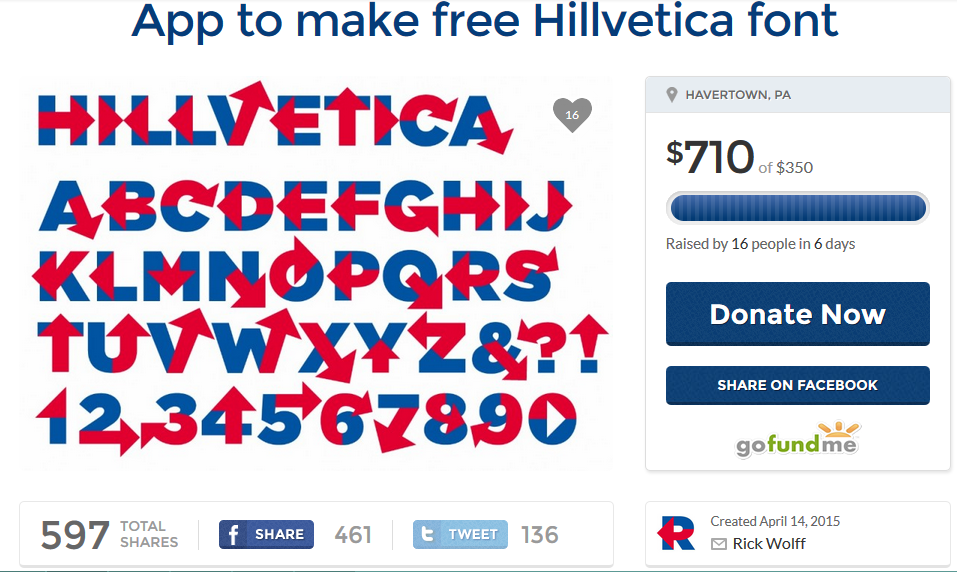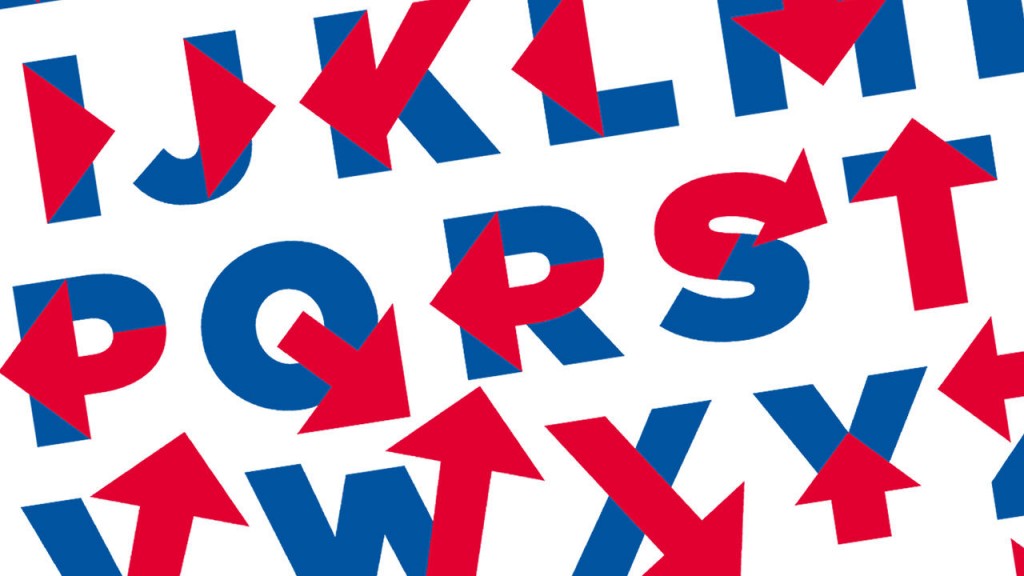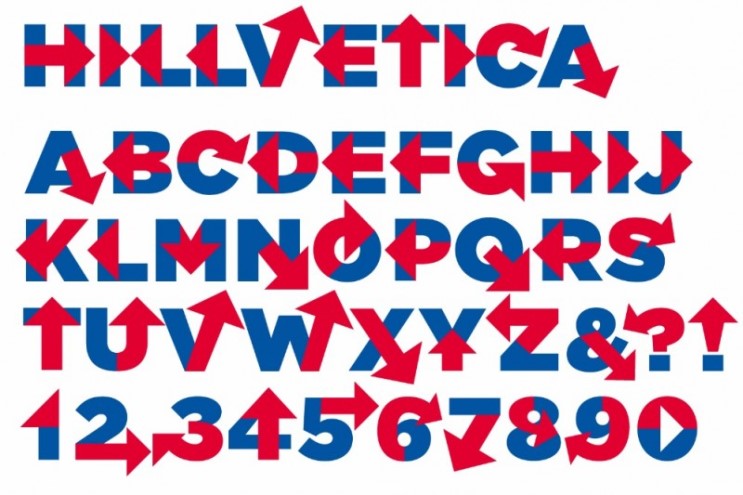
힐러리를 위한 폰트, 힐베티카(Hillvetica)
미국 대통령 후보를 뽑는 대선후보 경선도 어느새 막바지에 이르렀습니다. 이번 미국 대선도 점점 경쟁이 치열해짐에 따라 다양한 마케팅 기법이 동원될 것 같은데요, 그 중에서도 가장 먼저 눈에 띄는 것이 힐러리 캠프의 전용서체, 힐베티카입니다.
정치도 마케팅이다? 힐러리를 위한 폰트, 힐베티카(Hillvetica)
힐러리, 최초의 미국 여성 대통령이 될 수 있을까?
미국 대통령 후보를 뽑는 대선후보 경선도 어느새 막바지에 이르렀습니다. 중요한 분수령으로 평가받은 미니 슈퍼화요일 투표에서 민주당 힐러리 클린턴과 공화당 도널드 트럼프가 대승을 거뒀다고 며칠 전에 보도되기도 했었죠. 아마 큰 이변이 없다면, 지금의 예상대로 이 두 명의 후보가 미국 대통령을 사이에 두고 끝까지 경쟁을 펼칠 것 같습니다.
국제적으로 미국이 가지는 정치/경제적 위상이 워낙 커서 미국 대통령 선거가 중요하기도 하지만, 미국 대선은 당선을 위해 모든 마케팅이 동원되는 치열한 마케팅 현장이기도 합니다. 지난 2013년, 오바마의 재선을 위해서 빅데이터와 마이크로 타겟팅의 최신 마케팅 기법이 동원된 사례는 이미 널리 알려진 바 있습니다. 오바마가 최신 IT 기술을 동원해 빅데이터 전략을 취하고 있을 때 상대 후보인 롬니는 정보기술 관련 비용으로 300만 달러를 지출했는데, 이는 오바마가 지출한 3600만 달러의 1/10도 안 됩니다. 이미 승리는 결정된 바와 마찬가지였죠.
이번 미국 대선도 점점 경쟁이 치열해짐에 따라 다양한 마케팅 기법이 동원될 것 같은데요, 그 중에서도 가장 먼저 눈에 띄는 것이 힐러리 캠프의 전용서체, 힐베티카입니다.
이게 힐베티카의 모티브가 된 힐러리 캠프 로고입니다. 어떠세요?
힐러리 클린턴은 대선 출마선언과 동시에 대선기간 동안 사용할 캠페인 로고를 발표했습니다. 자신의 이름 첫 글자인 ‘H’를 활용해서 만든 로고인데요. 파란색을 기본으로 빨간색을 포인트로 활용하여 성조기를 표현함과 동시에 강하고 진보적인 느낌을 줍니다.
힐러리는 2008년 대선에서 오바마와 경선에서 맞붙으면서 오래된 정치인이라는 이미지를 얻게 되었습니다. 이러한 상황에서 전통적이고 뻔한 캠페인 로고는 진부한 정치인의 이미지를 줄 가능성이 크기 때문에, 이번 캠페인 로고는 일부러 더 강렬하게 만든 것 같습니다. 가장 눈에 띄는 붉은 화살표는 진부한 이미지를 탈피하고 앞으로 나아가는 진보적인 성향을 표현하려 한 것이 아닌가 생각됩니다. 다만 워낙 인상이 강렬해서 그런지 사람들 사이에서 호불호가 갈리며 놀리거나 패러디하는 반응들도 이어지긴 했습니다.
‘병원(Hospital)으로 가라’는 표시처럼 보인다는 지적도..
재밌는 것은, 힐러리의 로고가 발표되고 얼마 지나지 않아 릭 울프(Rick Wolff)라는 그래픽 디자이너가 그것을 본뜬 폰트를 만들어 SNS로 알렸습니다. 이 폰트를 개발해 앱을 만들겠다며 펀딩을 올린 건데요. 이 폰트는 처음에는 ‘힐러리 볼드’로 불리다가 사람들이 ‘힐베티카’라고 제안해서 이름이 바뀌었다고 하네요. 힐러리와 헬베티카를 합성해서 ‘힐베티카’라고 나온 것 같은데 참 기발한 이름입니다.
힐러리 + 헬베티카 = 힐베티카!
릭 울프는 자신의 이니셜인 ‘R’을 힐러리 로고에 착안해서 만들면서 이 프로젝트를 시작했다고 합니다. 그러다 힐러리를 지지(?)하는 마음이 더해져서 프로젝트가 완성된 것이라고 하네요. 힐러리 로고에 있는 붉은 화살표와 푸른색 알파벳을 적극적으로 사용해여 모든 알파벳과 숫자에 적용하고, 각 알파벳에 어울리고 화살표를 구부리거나 방향을 구성했다고 합니다. 다 만들고보니 힐러리의 느낌이 물씬 나는 힐러리를 위한 폰트, 힐베티카가 탄생한 것이지요.
힐베티카는 나오자마자 트위터에서 여러가지 반응들이 잇따랐는데, 어떤 디자이너는 화살표를 따라가다 시각적 재앙이 펼쳐진다며 악평을 하기도 했지만, 대체로 사람들은 흥미로워하는 반응입니다. 심지어 힐러리 클린턴도 이 폰트를 사용해 지지 촉구 메시지를 보내기도 했습니다.
힐베티카가 SNS에서 계속 이슈가 되자 워싱턴포스트는 힐베티카를 직접 쓸 수 있는 위젯을 제공했고, 이는 다시 트위터와 페이스북으로 공유되면서 더 많은 사람에게 알려지게 되었습니다. 힐러리 입장에서는 ‘손 안 대고 코 푼 격’이라고 할 수 있을 것 같은데요. 어찌됐든 이 힐베티카라는 폰트를 통해서 자신의 존재를 사람들에게 각인시키는 좋은 계기가 되지 않았나 싶습니다.
붉은 화살표가 난무하다보니 좀 눈이 아픈 건 사실..
이미 수많은 타이포브랜딩 사례가 말해주듯, 잘 만든 폰트 하나로 많은 것을 바꿀 수 있습니다. 힐베티카는 다소 장난스럽게 만들어진 폰트이긴 하지만, 힐러리 캠프가 추구하는 색깔과 개성을 잘 표현하고 있을 뿐만 아니라 크게 이슈가 되었다는 점에서 힐러리에게 더없이 고마운 폰트가 아닐까 싶습니다. 힐러리의 인생폰트, 힐베티카는 이 폰트를 만든 디자이너 릭 울프의 홈페이지를 통해서 다운받을 수 있습니다.